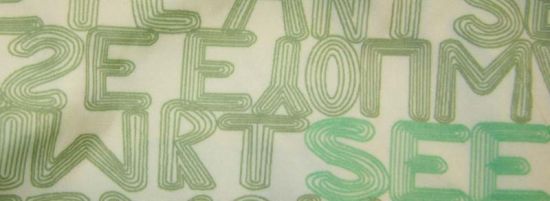
kann mir da jemand helfen? die schrift würde auf eine jacke verwendet et.........
sieht handgemacht aus, kann aber auch durch das nähen kommen. schau dir mal die E an.
das ist gedruckt, nicht genäht...
ich dachte nur - weils ddie schrfitart nun nicht sooo besonders ist, - jemand ev es evtl kennt
dann tippe ich auf handgemacht. Außerdem kommen dort kyrillische Glyphen vor, das macht es nicht einfacher. sorry, ich weiß es nicht.
das ist gedruckt, nicht genäht...
ich dachte nur - weils ddie schrfitart nun nicht sooo besonders ist, - jemand ev es evtl kennt
Suchst Du denn diese bewußt "schmutzige" Version oder kann's auch eine saubere sein:
Diese Prisma gibt es auch als digitalen Font.
he, danke! aber nicht ganz was ich suche. ich glaube du hast recht... -es sollte schon schmutzig sein.... ich bin für alles dankbar
wenns nur ein wort sein soll: selber stricken.
sollte aber schon das ganze alphabet werden. soll ein text-print werden mit einer 70x70 fläche ...